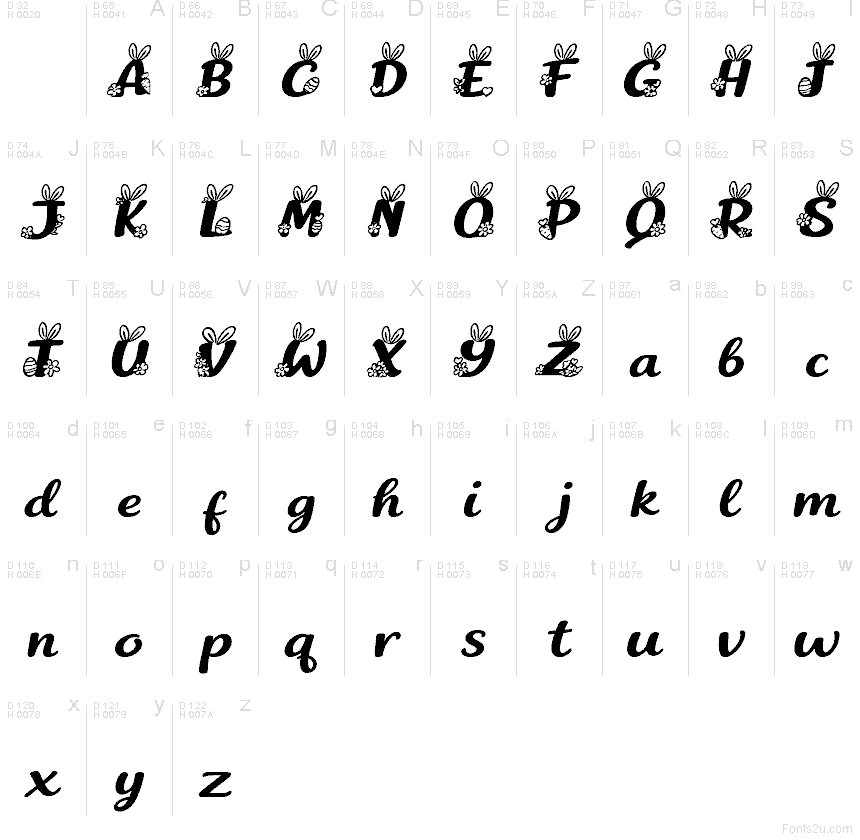
Easter Fabulous Italic Demo Italic
Easter Fabulous Italic de Yoga Letter é uma fonte script gratuita com temática de Páscoa, com um fluxo manuscrito inclinado e um design festivo. As letras apresentam formas suaves e arredondadas, com detalhes decorativos que lembram presentes, além de pequenos motivos florais e corações que conferem ao design um toque artesanal de estação.
Esta fonte gratuita funciona muito bem para cartões de Páscoa, convites de primavera, banners de feriados, panfletos, etiquetas de marcas e gráficos criativos para redes sociais, pois seus detalhes temáticos carregam um tom claramente comemorativo. Também é ideal para acentos em logotipos e citações decorativas quando você deseja que o estilo pascal se destaque sozinho, sem a necessidade de ornamentos extras.